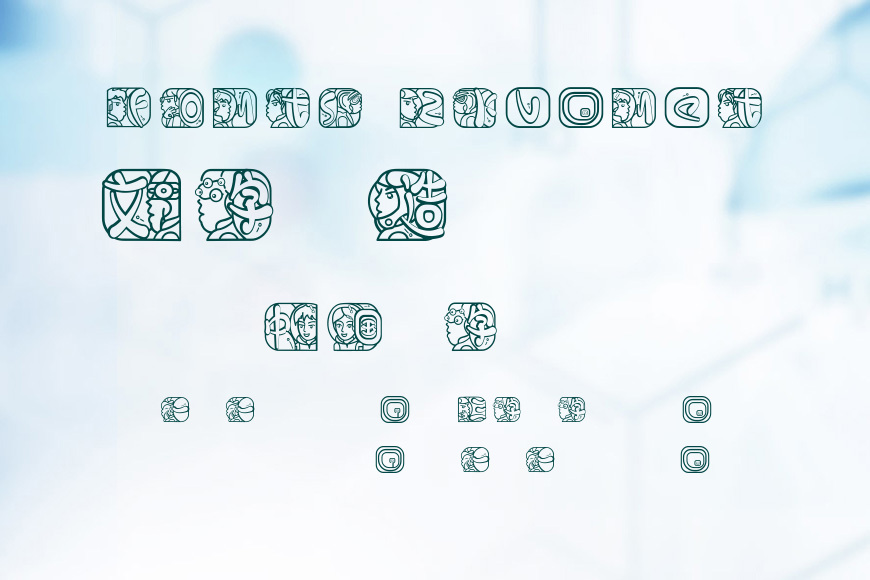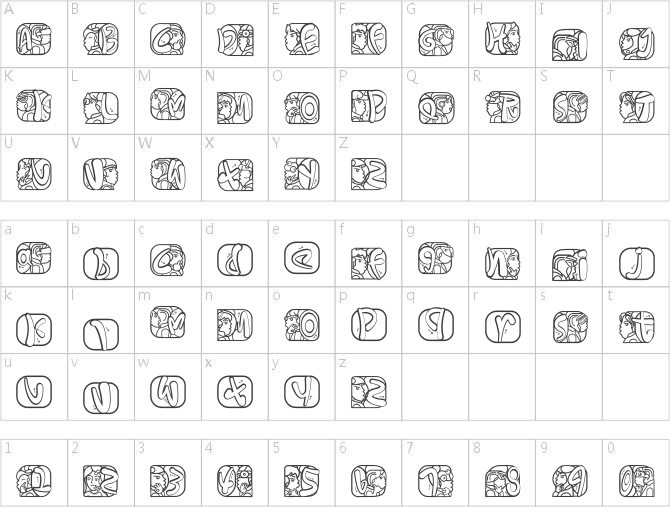
字体名称: IPfonts
IP fonts 是卡通动漫体外语版本由卡通动漫为灵感设计的一款卡通动漫IP字库,采用卡通动漫与文字的组合分布排列而成,让文字瞬间进入漫画状态。应用于字漫画、猜字谜、动漫文、数字爱情、趣味编程等等多方面。
IPfonts字体字库是一款让人赏心悦目、百看不厌的英文字体,适合各类广告和产品包装设计应用,字体大小0.19MB,格式为ttf字体,上传用户是sunlight,作者/版权方为小欣大萌